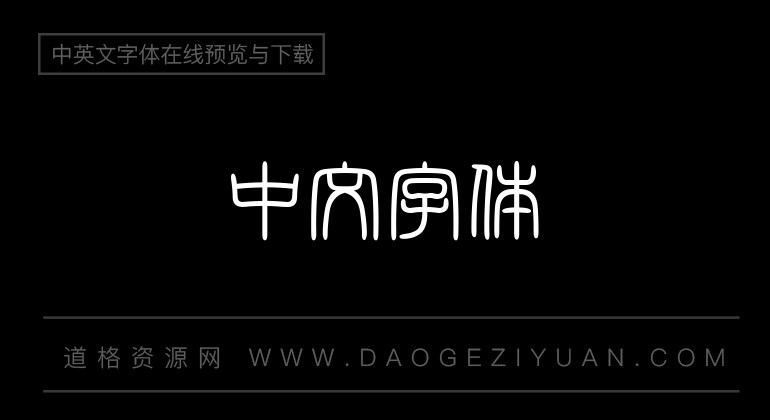
白舟太篆书体粗
白舟太篆书体粗是一种中国传统的字体,字体风格源自于秦代太篆,是由古代书法家白舟(1068-1151)创作的。字体特点是笔画粗细稳定,字形结构清晰,结构完整,笔画流畅,笔画粗壮,笔画细腻,笔画有力,字体格式大气,有着浓郁的古典气质。
白舟太篆书体粗是一款非常不错的手写艺术字体,具有很好的视觉感,适合于文化类的宣传设计、商业类品牌的广告和产品包装设计以及个性化文字排版等较多场景。